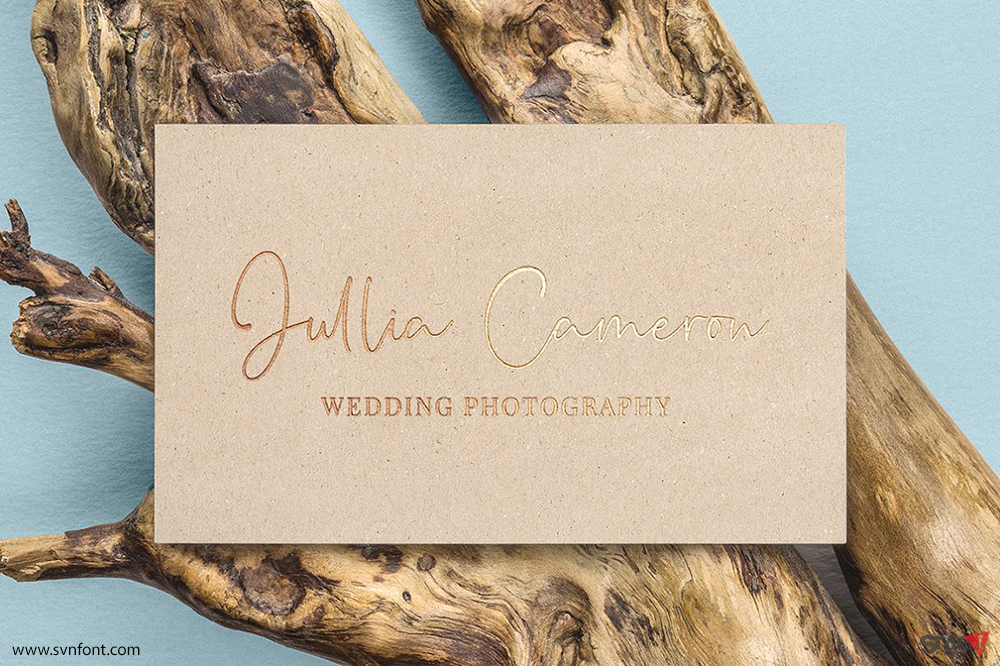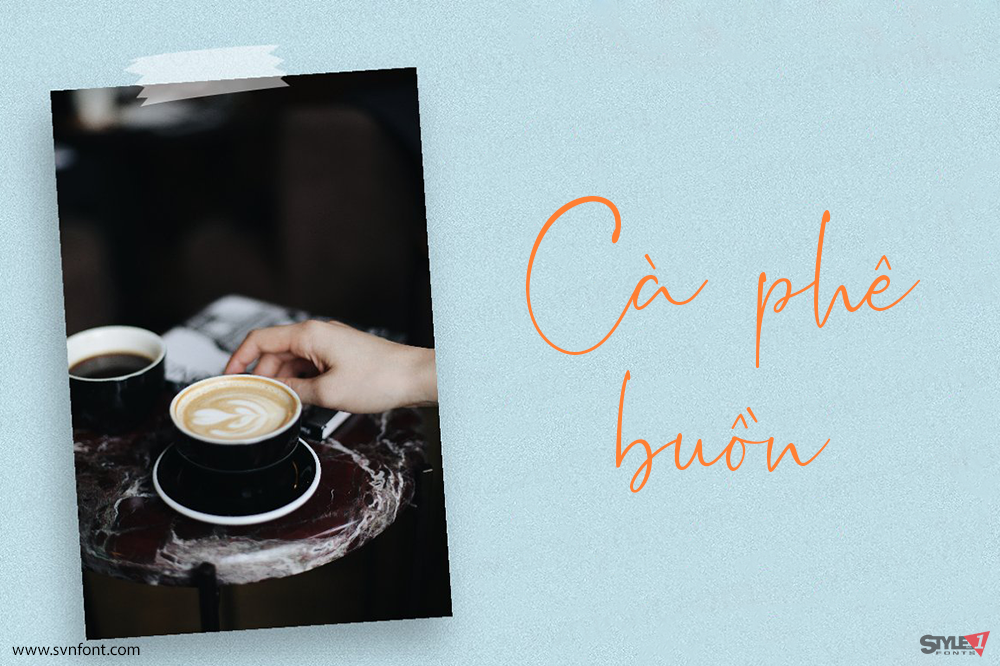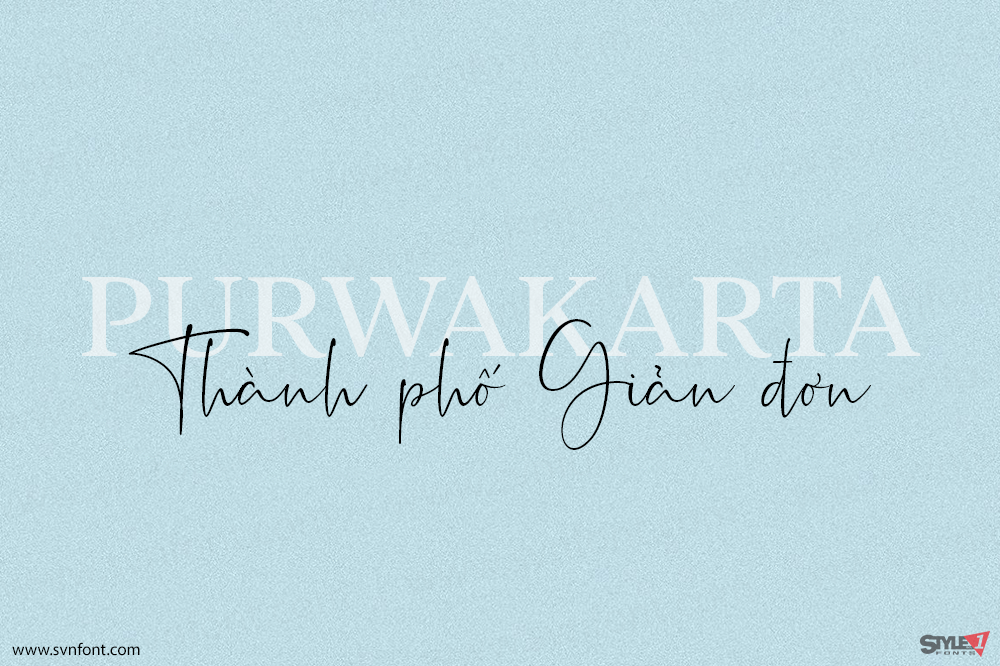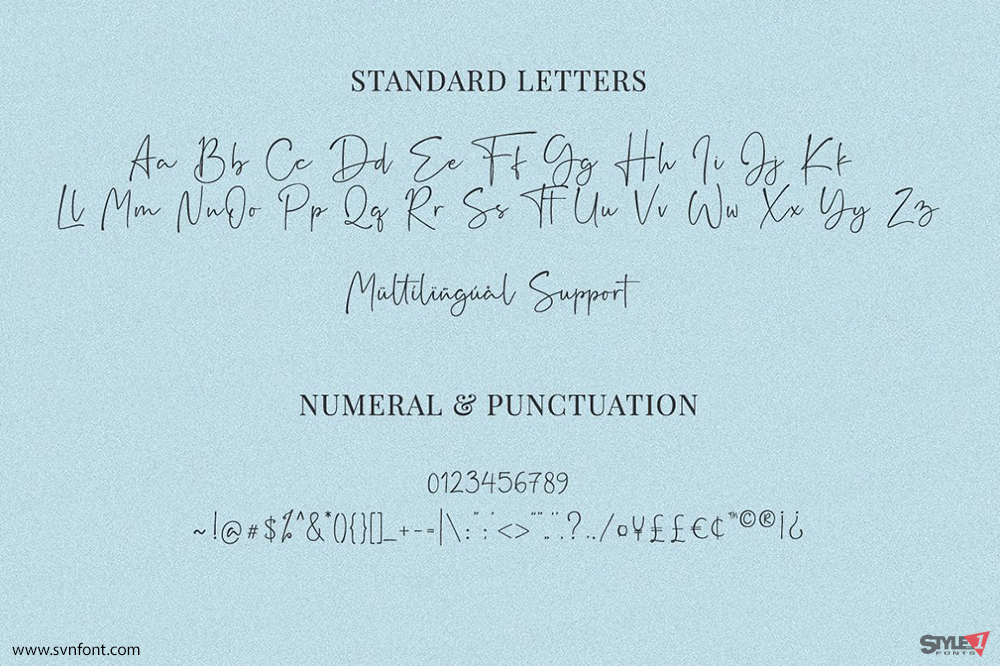
Rushtick là một font chữ signature mang phong cách tinh tế và sang trọng, rất phù hợp cho thiết kế bao bì, branding, mạng xã hội, blog và thiệp.
Rushtick hỗ trợ 13 ngôn ngữ, bao gồm đầy đủ chữ hoa, chữ thường, dấu câu, chữ số cùng 97 ligature được thiết kế đẹp mắt, mang lại khả năng trình bày linh hoạt và giàu tính thẩm mỹ cho các dự án sáng tạo.